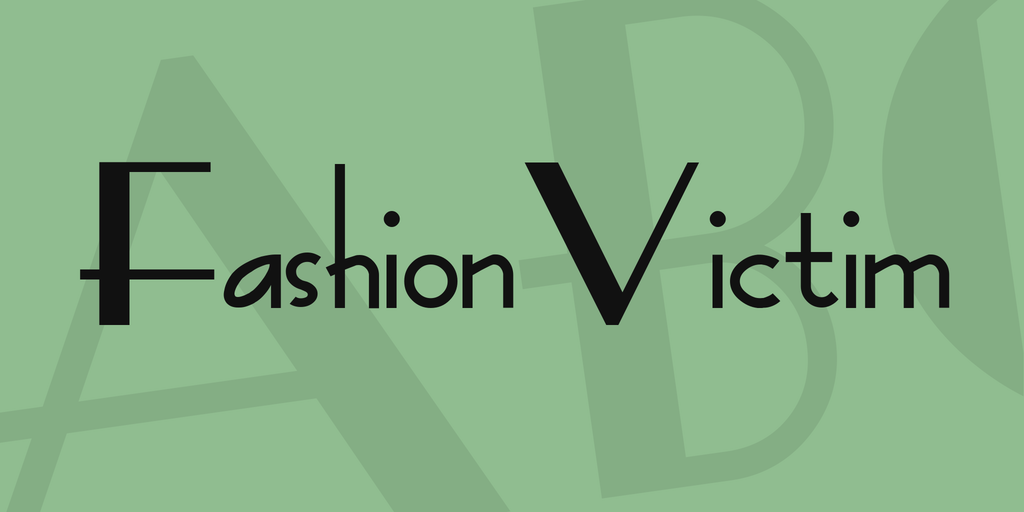
A FashionVictim Font é uma versão desafiada do Bernhard Fashion, oferecendo uma nova visão vibrante para os designers que buscam uma mistura arrojada e elegante. Inspirado no estilo sofisticado de Bernhard, mas com um toque mais contorneado e artístico, a FashionVictim foi projetada por Hamilton para fornecer uma opção de fonte de tipo Display que combina elementos modernos e clássicos. Essa nova versão mantém o charme da elegância do Bernhard, mas adicionalmente oferece um acabamento mais densoado e personalizado. O Deco-fied (ou decó) estilo adicionado ao design faz dela uma escolha ideal para qualquer projeto que busca um toque de sofisticação com certa dose de modernidade, seja em materiais digitais ou impressos. Esta fonte atua como um instrumento versátil, apto a estilizar títulos e headlines de maneira impressionante, proporcionando uma experiência visual interessante para qualquer projeto de design gráfico que busque uma personalização única.